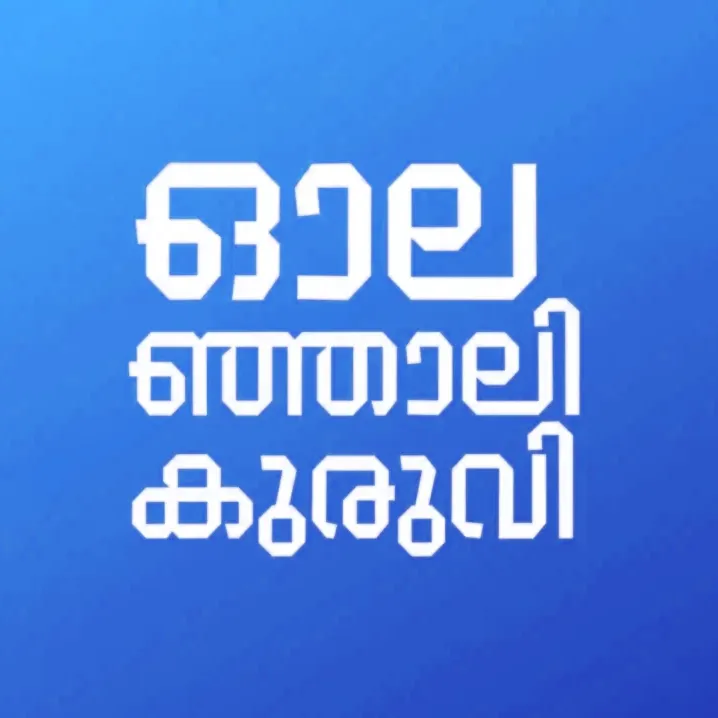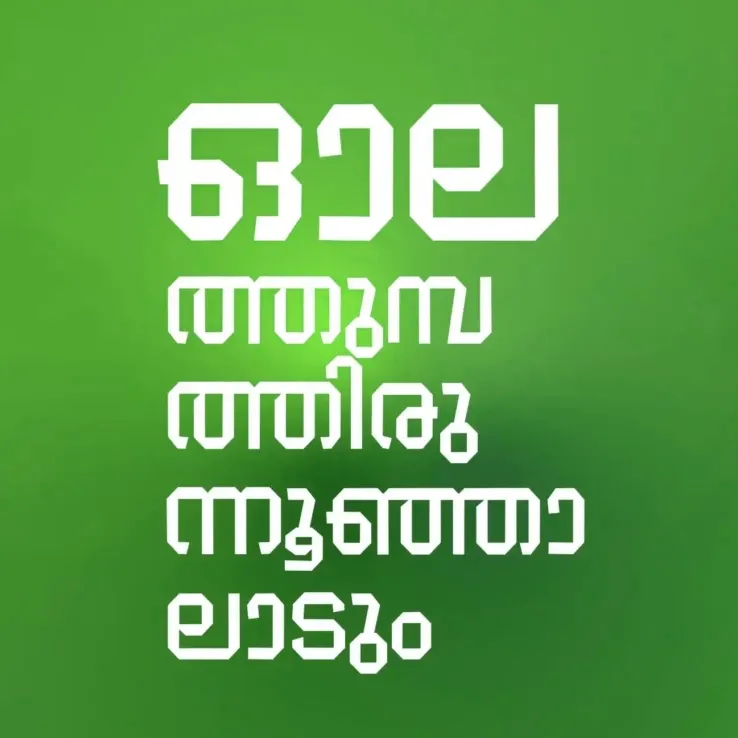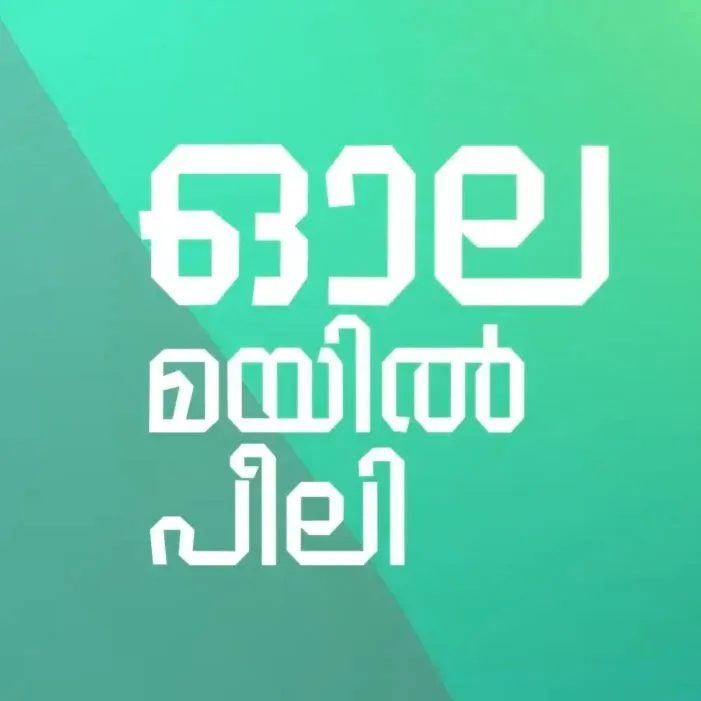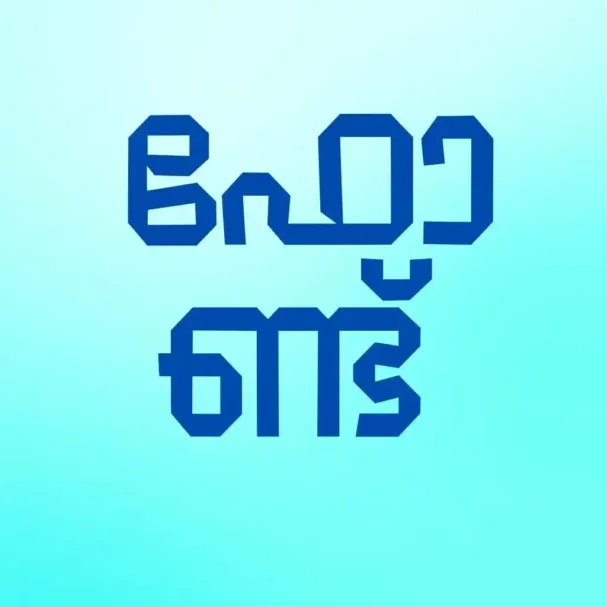
Ola Malayalam Font (ഓല ഫോണ്ട്) | Free Traditional Font
നമ്മുടെ നാടിന്റെ പ്രതീകമായ തെങ്ങിന്റെ ഓലയുടെ മനോഹരമായ രൂപത്തിൽ നിന്ന് പ്രചോദനം ഉൾക്കൊണ്ട് നിർമ്മിച്ച ഒരു ഫ്രീ മലയാളം ഫോണ്ടാണ് "ഓല". ഓരോ അക്ഷരത്തിലും ഓലയുടെ തനിമയാർന്ന ശൈലി വായനക്കാർക്ക് പുതിയൊരു അനുഭവം നൽകും. 100% സൗജന്യമായി ഡൗൺലോഡ് ചെയ്യാവുന്ന ഈ ഫോണ്ട് രൂപകല്പന ചെയ്തിരിക്കുന്നത് കലാകാരനായ SUMEESH ആണ്.